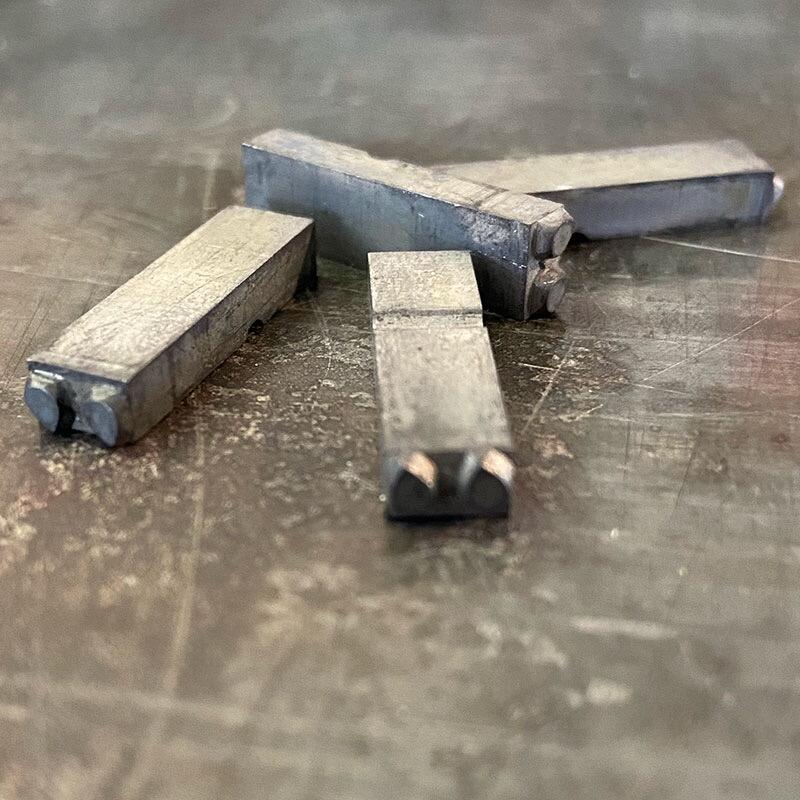
Der breitenlose Verbinder (Unicode: ZERO WIDTH JOINER) ist ein standardisiertes Sonderzeichen, mit dem sich im Unicode kodieren lässt, dass zwei getrennt kodierte Zeichen als Ligatur zu verbinden sind. Das Zeichen bildet damit das Gegenstück zum Bindehemmer. Das Zeichen kann zum Beispiel in arabischen und indischen Schriftsystemen verwendet werden. Auch für die Kodierung von Frakturtexten nach klassischen Satzweisen können Bindehemmer und breitenloser Verbinder eingesetzt werden, um di
Die menschliche Wahrnehmung spielt uns bei der Einschätzung dieser Objekte einen Streich. Kreis und Dreieck scheinen eine etwas kleinere Höhe zu besitzen, obwohl alle Objekte exakt gleich hoch sind. In der Gestaltung von Schriftarten muss diesem Effekt durch einen optischen Ausgleich entgegengewirkt werden. Spitzen und Rundungen werden dazu mit einem Überhang (englisch: overshoot) versehen. Die betreffenden Stellen ragen dann mehr oder weniger stark über Grundlinie, x-Höhe oder Versalhöhe h
Übersetzer nennt man im Bleisatz die diakritischen Zeichen, welche Versalien größerer Schriftgrade zu Umlaut- und Akzentzeichen verwandelten. In einigen Schriften wurden zusätzlich Kleinbuchstaben in verkürzter Größe geliefert, die zur Aufnahme dieser Übersetzer bestimmt waren. Schriftmuster mit Verweis auf die enthaltenen Übersetzer in größeren Schriftgraden
Das Umbrechen (auch der Umbruch oder die Mettage) ist das Einteilen des Satzes in die endgültigen Kolumnen und Seiten. Insbesondere im Zeitungssatz bildete diese Tätigkeit eine eigene Berufsgruppe (siehe Metteur).
Die vier Umschlagseiten werden mit U1 bis U4 bezeichnet. Das erste, was man von einer Publikation, sei es nun Buch, Zeitschrift oder sonst etwas, sieht, ist die Seite U1. Schlägt man das Werk auf, schaut man links auf die, bei Büchern in der Regel unbedruckte, Seite U2 (und bei Büchern rechts dann auf den Schmutztitel). Blättert man nun das ganze Werk durch, bis man die letzte Seite umgeschlagen hat, dann ist links die letzte Seite des Werkes und rechts liegt U3, bei Büchern meistens ebenf
Der englische Begriff Unicase bezeichnet Schriften oder Schriftsysteme, die nicht wie die lateinische Schrift in gemischter Schreibung über dedizierte Groß- und Kleinbuchstaben-Sets verfügen. Beispiele für Schriftsysteme dieser Art sind zum Beispiel Arabisch oder Hebräisch. Im Deutschen lassen sich diese Schriftsysteme auch als »einhäusig« beziehungsweise »monokameral« bezeichnen. Benutzt man den Begriff Unicase innerhalb der lateinischen Schrift, ist damit eine besondere Art der Schri
Die »Unicode-gerechte Norm für Zusatzzeichen« (abgekürzt UNZ) ist eine Empfehlung zur Kodierung spezieller Schriftzeichen (insbesondere Ligaturen). Die Empfehlung wurde von Mitgliedern des Bundes für deutsche Schrift und Sprache (BfdS) entwickelt und mit der »Medieval Unicode Font Initiative« (MUFI) und dem Projekt »Thesaurus Indogermanischer Text- und Sprachmaterialien« (TITUS) abgestimmt. Hintergrund: Typische Ligaturen des klassischen Fraktursatzes (zum Beispiel ch/ck/ll/tt) haben im Unicod
Unique ID und XUID sind Identifikationsnummern für PostScript-Type-1-Fonts. Sie dienen dazu, Fonts in PostScript-Druckern über mehrere Druckaufträge hinweg zwischenzuspeichern. Unique IDs gelten als veraltet und werden nicht mehr neu vergeben. Eine XUID (»Extended User ID«) ist ein 10-stelliger Kode. Die ersten vier Stellen sind die Herstellerkennung. Diese muss bei Adobe angefordert werden. Die restlichen Stellen können frei zur Kennung von Schriftfamilie und Schnitt verwendet werden, wobei me
Der Universal Type Server ist eine Schriftverwaltunglösung für Unternehmen. Extensis stellt damit den Nachfolger der Produktlinien Suitcase Server und Font Reserver Server vor. Das von Grund auf neu entwickelte Programm verwaltet Fonts und Fontlizenzen netzwerkbasiert und wird über eine einfache Browseroberfläche bedient. Der Universal Type Server ist in zwei Varianten verfügbar: die Professional-Version ist für Arbeitsgruppen jeder Größe bestimmt, die Lite-Version für Teams mit bis zu 10 Arbeit
Die Unterlänge ist der Teil eines Kleinbuchstabens, der unter der Grundlinie liegt. Sie reicht bis zum unteren Ende des physischen oder virtuellen Schriftkegels. Die Unterlänge liegt in der Regel etwas unterhalb der sichtbaren Begrenzung von Buchstaben wie g und y, steht aber damit nicht in direktem Zusammenhang. Man kann also von der Buchstabenform selbst nicht auf die genaue Lage der Unterlänge des Schriftkegels schließen.
Der Abstand eines Buchstabens zu den benachbarten Zeichen wird in erster Linie durch die Breite (Dickte) des Schriftkegels bestimmt. Einige Buchstabenkombinationen benötigen darüber hinaus einen speziellen Ausgleich des Abstandes. Im Bleisatz mussten die Lettern physisch beschnitten werden, damit beispielsweise im Wort »Telefon« das »e« unter den Querstrich eines »T« geschoben werden konnte. Daher rührt die Bezeichnung »Unterschneidung«. Ohne Unterschneidung (links) und mit Unterschneidung (